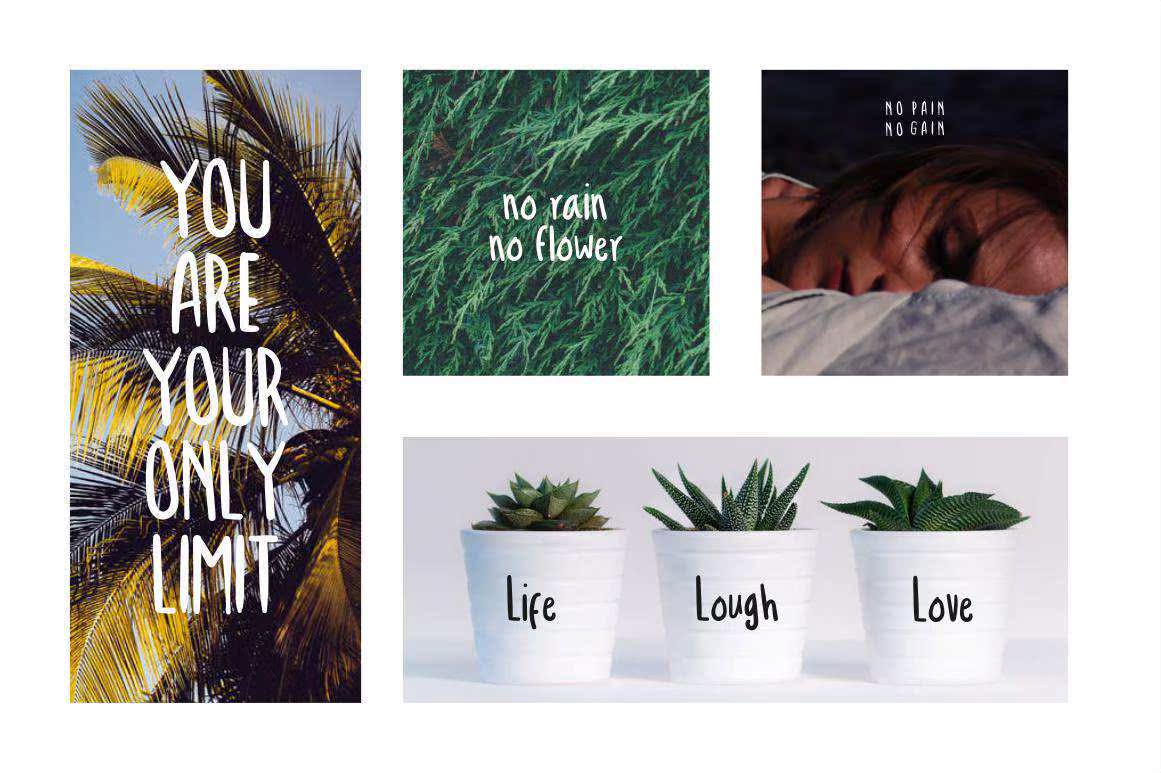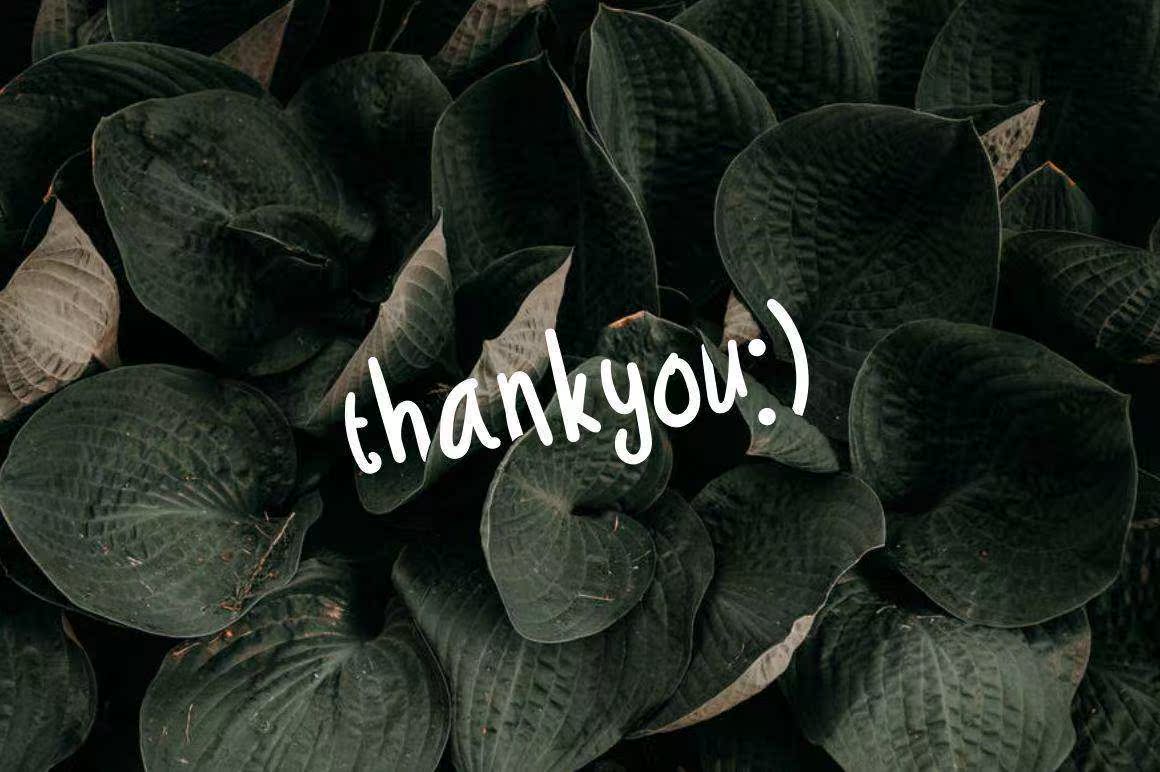
Troficanos是一款具有完美性格、孩子、善良、完美婚礼形象、派对、网站、广告、产品标签,或任何像Troficanos字体一样需要的和有趣的触感的手写字体。Troficanos是一款具有完美性格、孩子、善良、完美婚礼形象、派对、网站、广告、产品标签的手写字体,或任何需要的东西,如Troficanos字体。